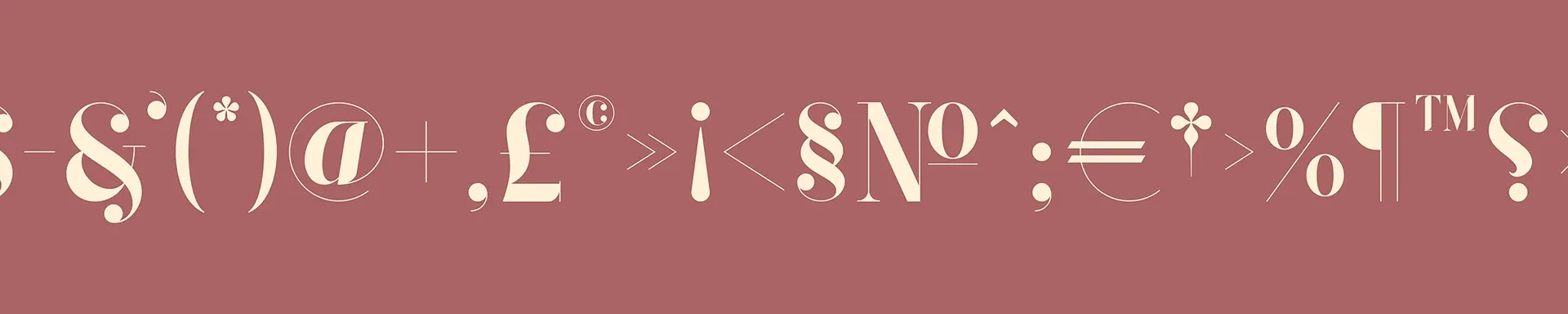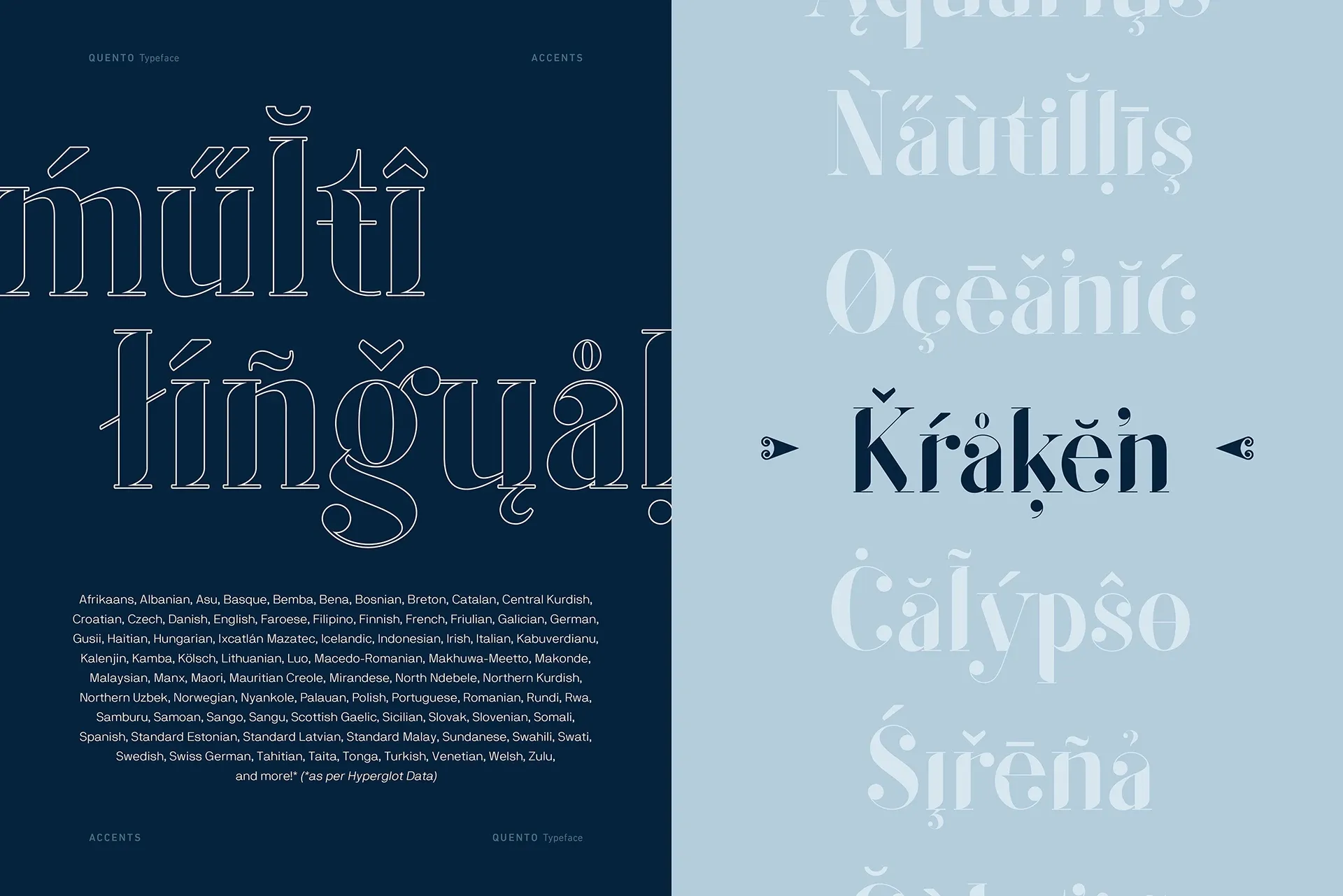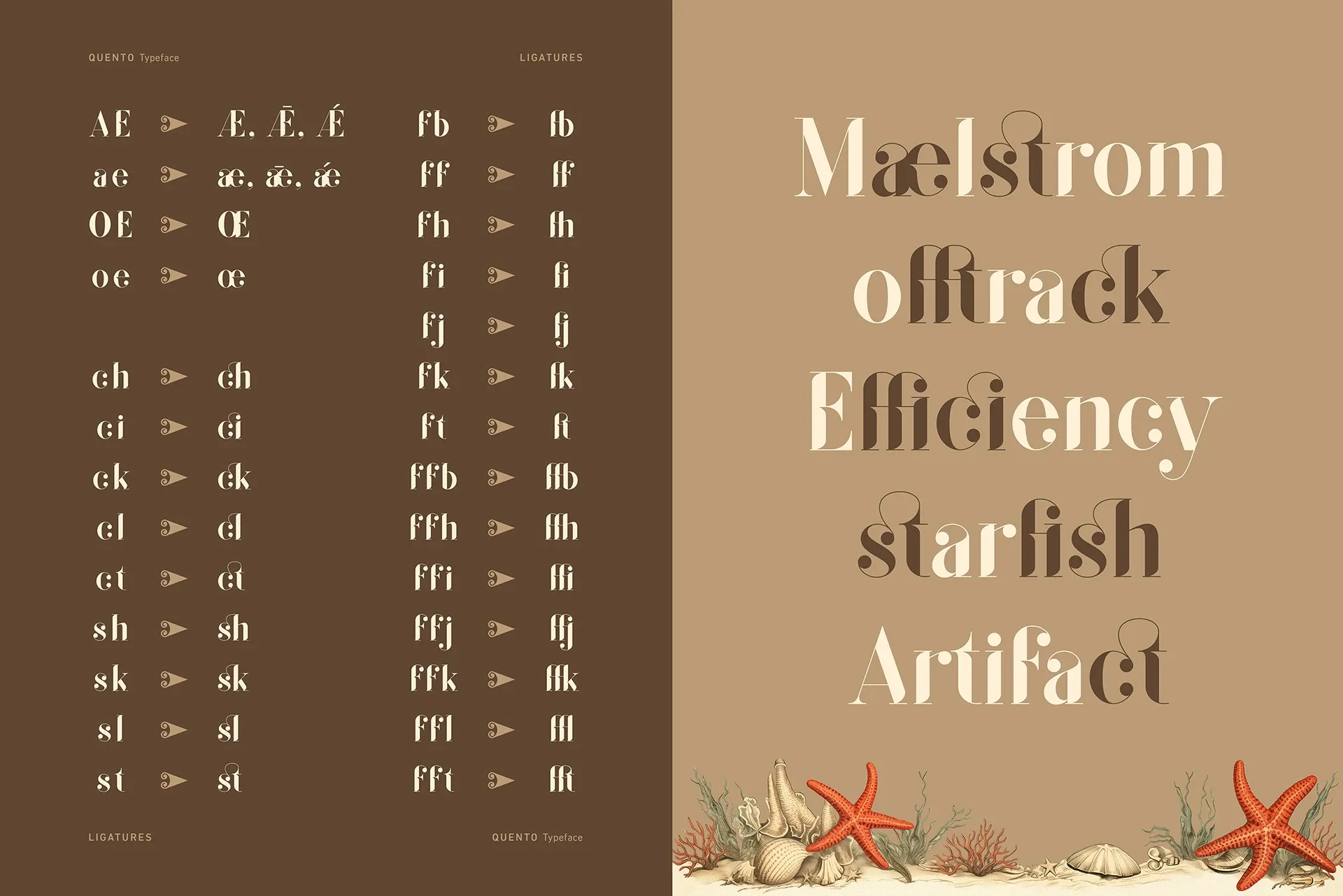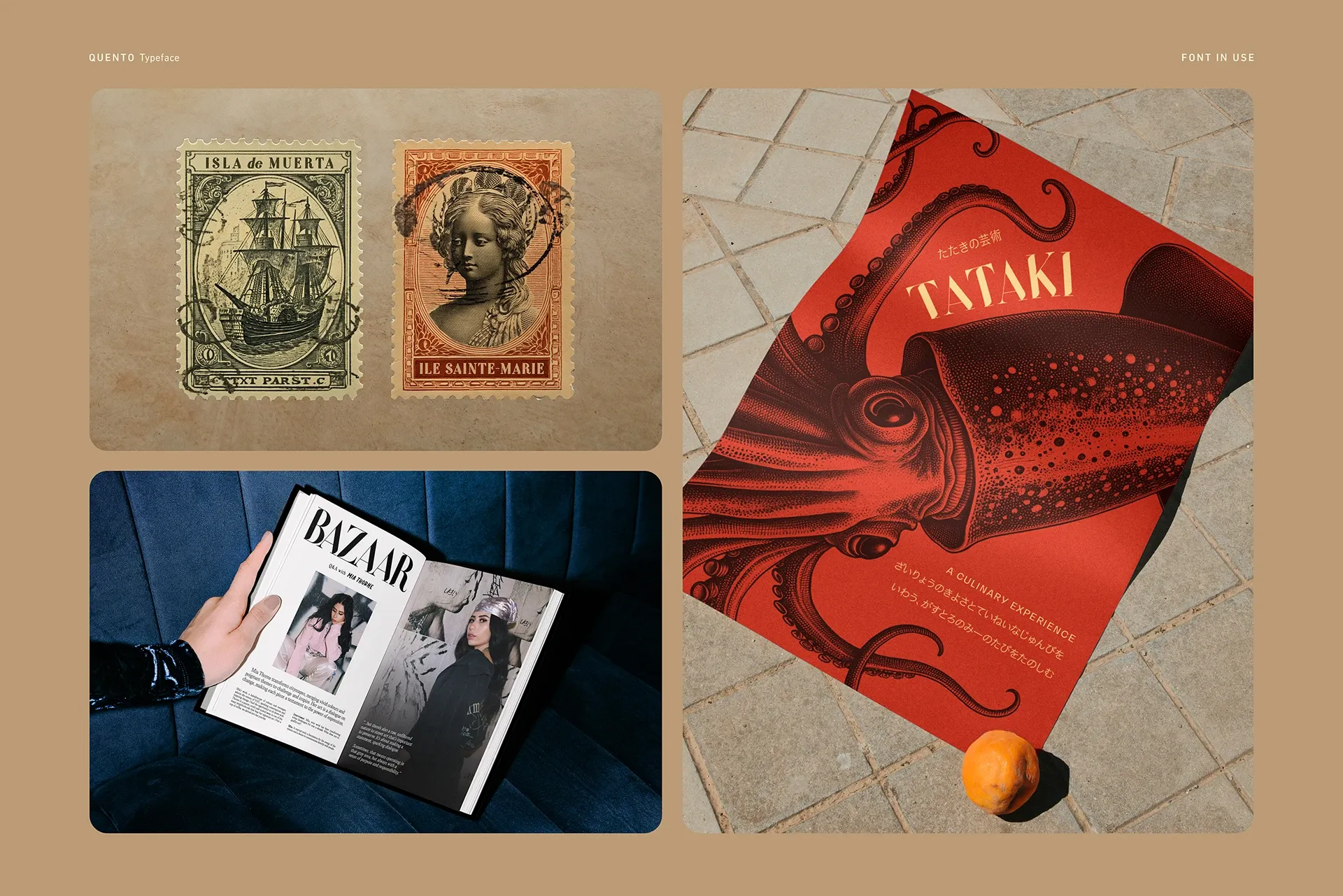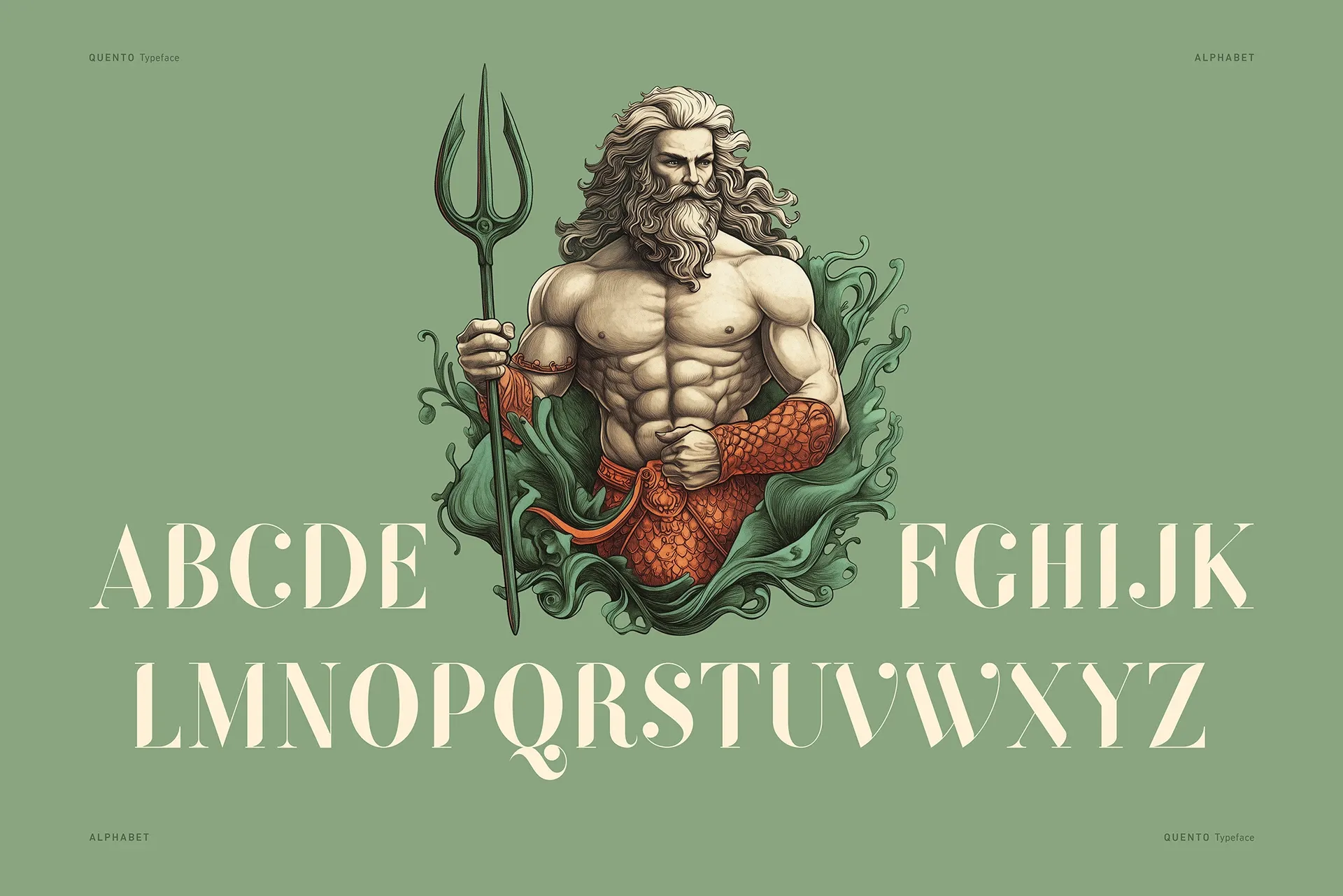
QUENTO là một typeface display Didone được thiết kế bởi Kimmy Lee và Petros Afshar. Nó sở hữu sự tương phản nét (stroke contrast) cực độ, trục dọc chân thật (true vertical axis), và hơn 550 glyph, lý tưởng cho các tiêu đề báo chí.
QUENTO là một typeface display Didone được xây dựng trên một cam kết cấu trúc duy nhất. Độ dày của nét ngang (hairline horizontals) chỉ từ 1–2pt optical weight so với các nét dọc gần 90pt — độ tương phản nét là tuyệt đối, không phải là sự ước lượng. Các đầu nét trên chữ a, c, f, r, và y tạo thành hình giọt nước được căn giữa về mặt thị giác. Ở quy mô tiêu đề, chúng trông giống như dấu câu, chứ không phải là đồ trang trí. Góc độ căng nằm ở trục dọc thực sự, 0°. Chính trục thẳng đứng cứng nhắc này tạo nên sự khác biệt của QUENTO so với các serif nghiêng kiểu oldstyle. Kimmy Lee và Petros Afshar trình bày thiết kế này ở dạng đơn sắc thuần túy — chữ đen trên nền trắng, hoặc trắng trên đen. Không có màu sắc nào làm phân tâm khỏi cấu trúc của nó.
QUENTO Display Typeface: Tương Phản Nét cho Tiêu Đề Báo Chí
Truyền thống Didone kéo dài từ Bodoni và Didot đến hàng thập kỷ các tiêu đề tạp chí và thương hiệu xa xỉ. QUENTO điều chỉnh lại truyền thống này cho các độ phân giải màn hình mà các bản gốc không được thiết kế. Bộ 550+ glyph bao gồm các ký tự Latin mở rộng, ligatures và dấu phụ — đây là một thiết kế typeface display đang hoạt động, không chỉ là một sự mới lạ trang trí. Một bản demo miễn phí giúp bạn kiểm tra nó trước khi cam kết sử dụng. Bản phát hành thương mại đầy đủ còn hỗ trợ dàn trang đa ngôn ngữ.